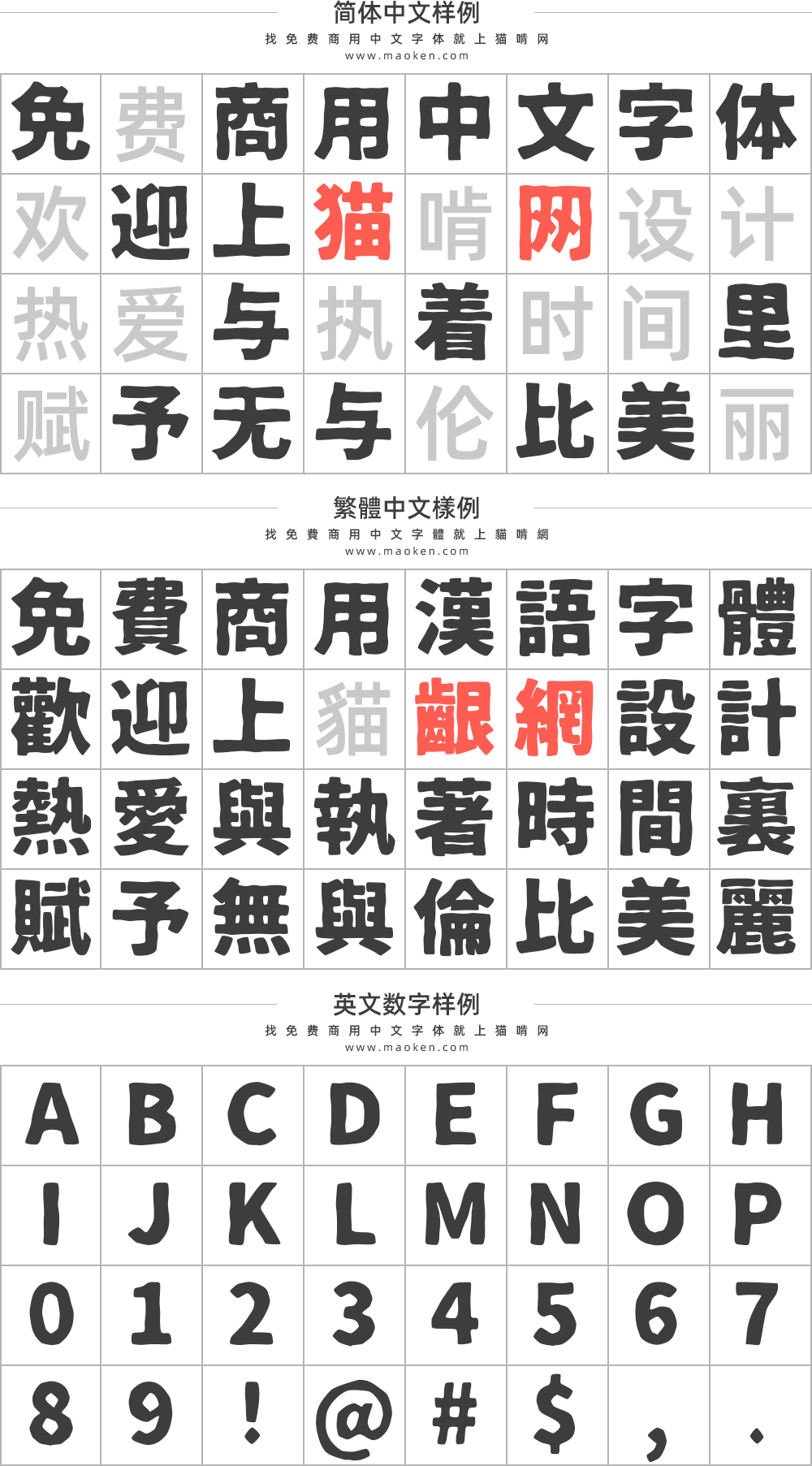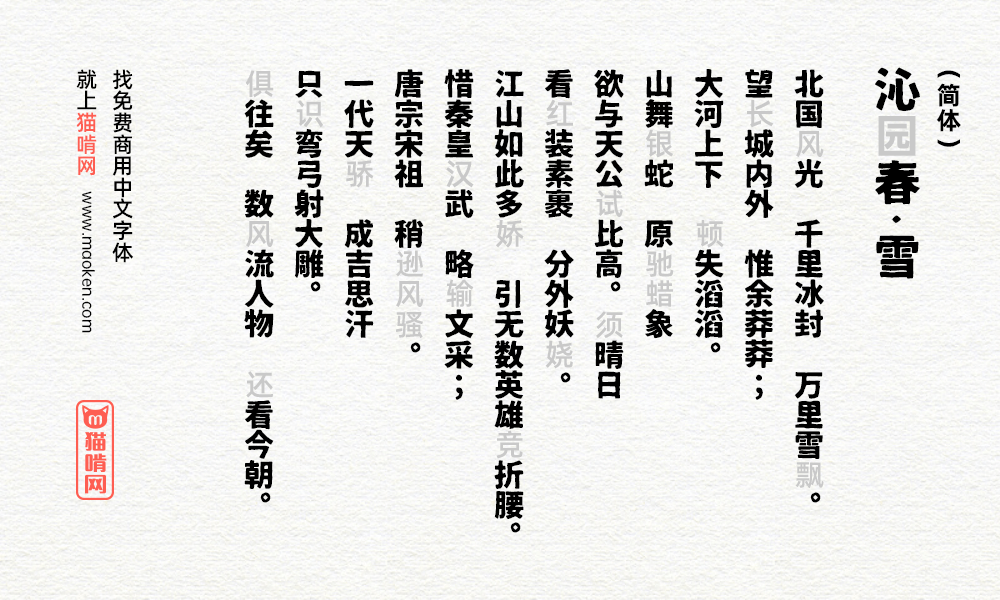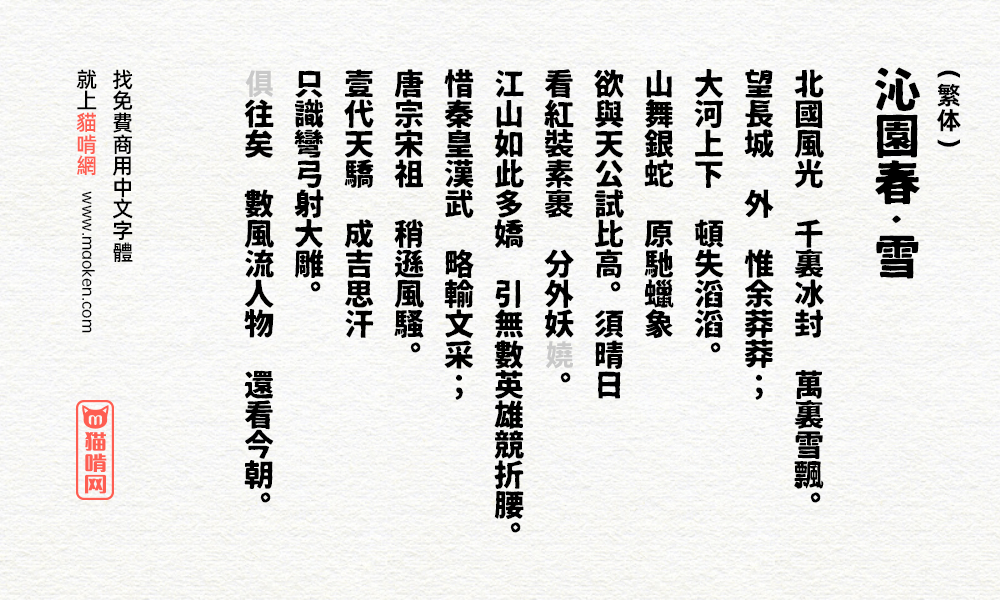
「铁瓶黑体」(日文名:鉄瓶ゴシック)以日本版的「思源黑体」(日文名:源ノ角ゴシック)为基础制作的派生字体,其字体版权是按照“Apache License 2.0”的许可进行。无论是商用还是非商用都可以使用,请放心下载。
字体特色
「铁瓶黑体」的设计比较有特色,字体边上加上了不平整的设计,让字体看上去十分有趣味。这款字体比较适合用于LOGO,偏刚性的海报设计。不过由于是日本设计师设计的字体,所以对简体中文支持不算太好。但是繁体的字型却是比较齐全。这款字体收录汉字约5300个 (JIS第1水准2965字,第2水准3390字) 。